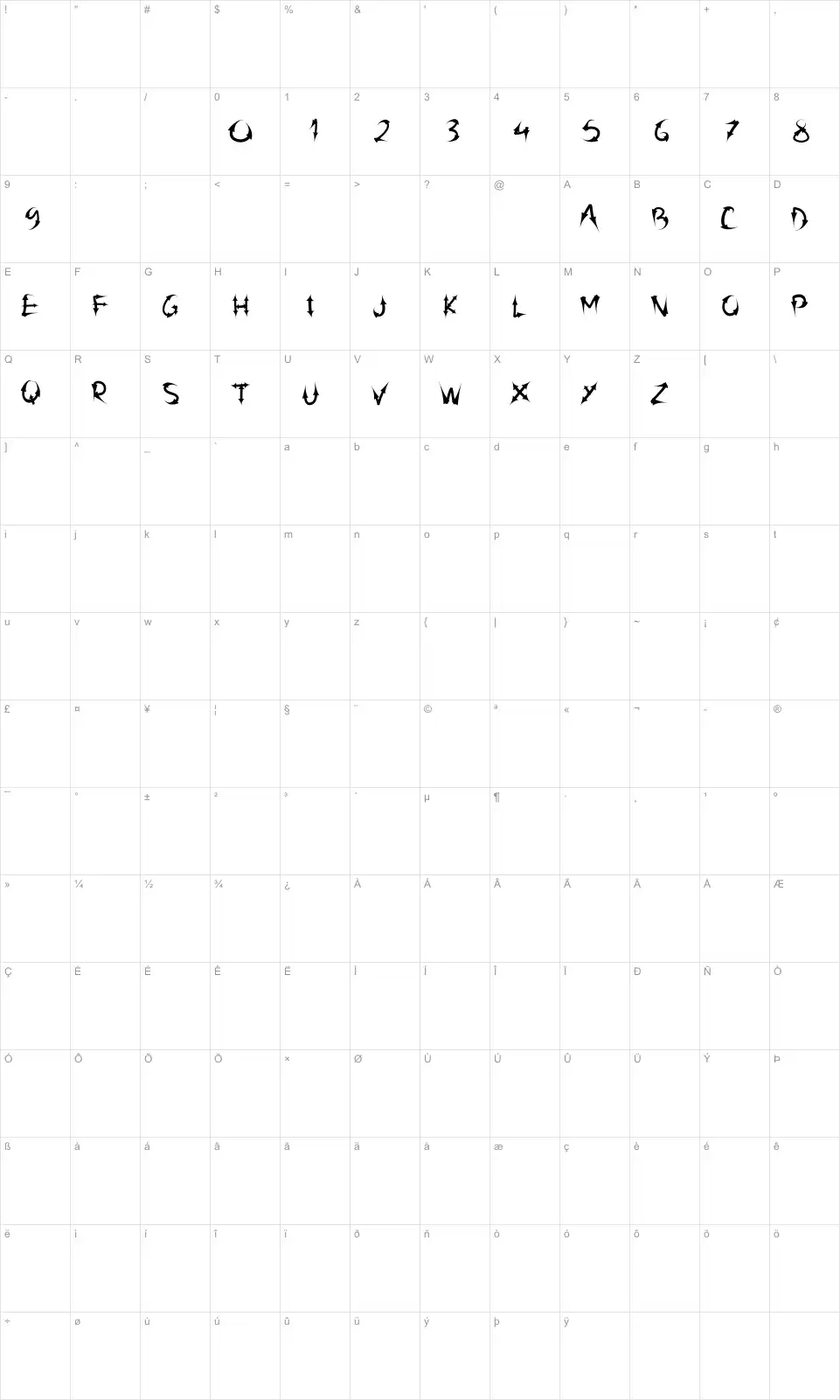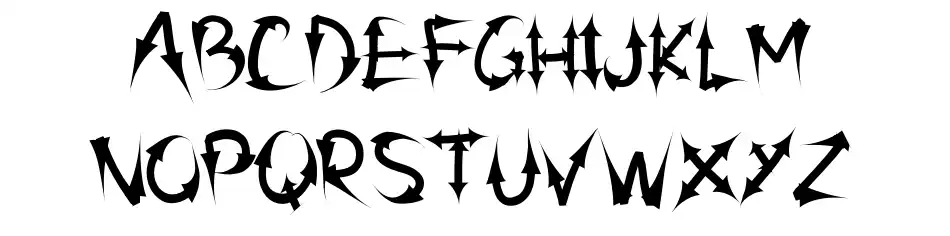
PW Arrow font – Fonte Grátis
PW Arrow font
A PW Arrow é uma fonte Gothic ideal para criar design gráfico moderno e sofisticado. Desenhada pelo Icon Designer, esta font oferece uma variedade de opções que vão do básico ao mais elaborado, dependendo da sua necessidade. Se você está à procura desta fonte, agora é a hora de ter acesso a ela e ver como ela se adapta aos seus projetos. Se você ainda não tem certeza sobre como a PW Arrow vai funcionar, você pode experimentar gerar um preview personalizado de texto online para ter uma ideia clara antes de começar a usar. A fonte está disponível em formato TTF e tem uma licença gratuita para uso pessoal. Com downloads atingindo 1615, esta fonte já está fazendo parte dos projetos de muitos designers gráficos. Com uma categoria específica de Gothic, a PW Arrow é uma escolha ideal para quem busca algo mais robusto e marcante em seu design. Se você é um entusiasta do design e está procurando por fontes de qualidade, a PW Arrow provavelmente será uma fonte que você vai querer ter em sua coleção. Visite o site do designer, https://www.icon-designer.fr, para mais informações e recursos sobre esta fonte.
Designer: Icon Designer